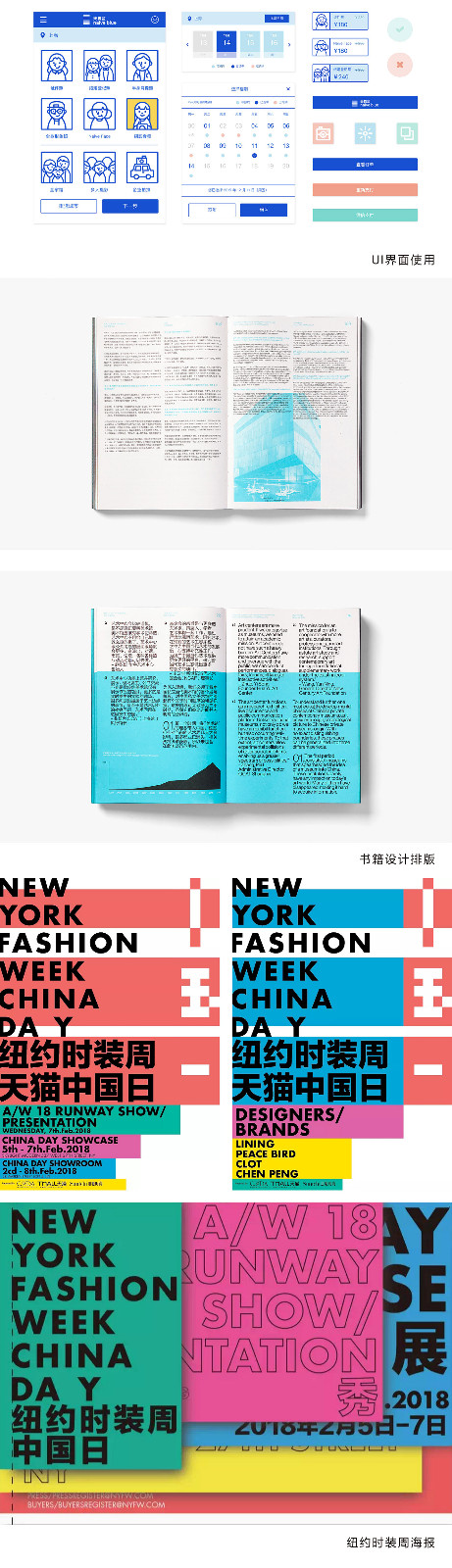
方正兰亭黑Pro Global
方正兰亭黑Pro Global,这款字体结构工整、笔画清晰,兼顾美观与易读性,适用于标题、正文、海报、包装、LOGO 等多种场景。字形优雅稳定,风格百搭耐看,适配日常排版与创意设计,让文字呈现更舒适、更具质感。方正兰亭黑Pro Global一笔一画,皆是细节,以均衡的比例、流畅的线条打造舒适视觉体验,字形端正大气,风格简约现代。无论是商业设计、品牌宣传还是日常排版,都能轻松驾驭,让文字更有格调与力量。方正兰亭黑Pro Global字体下载。
中国人方正字,中国属于世界的,而世界也是中国的。方正兰亭黑Pro Global家族字体是方正字库的第一款全球字库,目前发布的第一个版本拥有八个字重,支持语言达到了200多种语言,包含中文,拉丁文,西里尔文,希腊文,阿拉伯文。该字体为数字媒体的跨平台应用带来更优秀的体验,是方正字库与国际字库厂商合作的一次有益尝试。